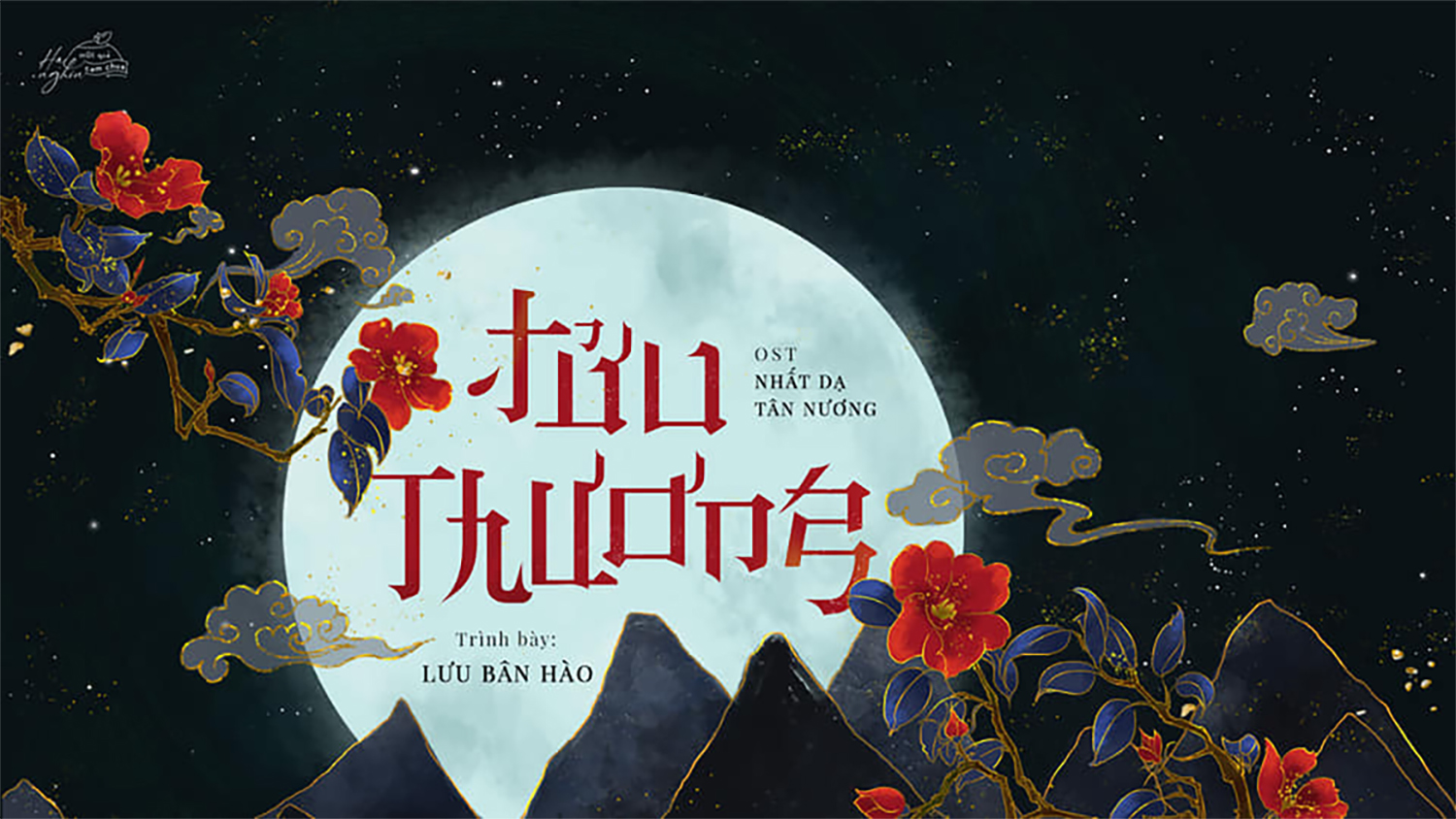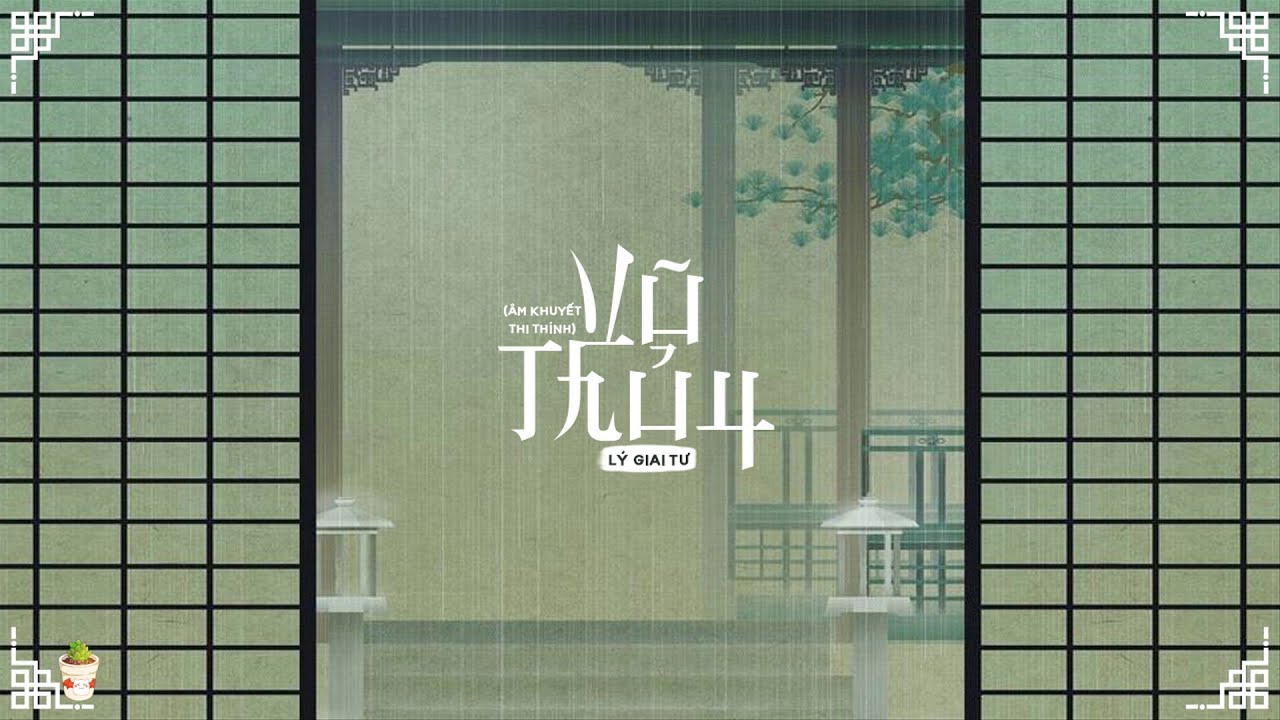
Font KZ Bladerunner Việt Hóa – Font chữ cổ trang
Font chữ KZ Bladerunner Việt Hóa đây là kiểu font chữ Nhật Bản khá phù hợp với các thiết kế cổ trang, font được Việt Hóa hoàn chỉnh và chỉnh sửa lại kenring, features đầy đủ.